B.プレミアに参入決定のプロバスケットボールチーム・滋賀レイクスのリブランディングで和文フォントにモリサワの新ゴが採用
モリサワの代表的なフォントのひとつである「新ゴ」が、B.LEAGUE(Bリーグ)所属で、2026-27シーズンから始まる新しい男子プロバスケットボールのトップリーグ「B.LEAGUE PREMIER(B.プレミア)」への参入が決定した「滋賀レイクス」の和文オフィシャルフォントとして活用されていることを2024年10月23日に発表した。
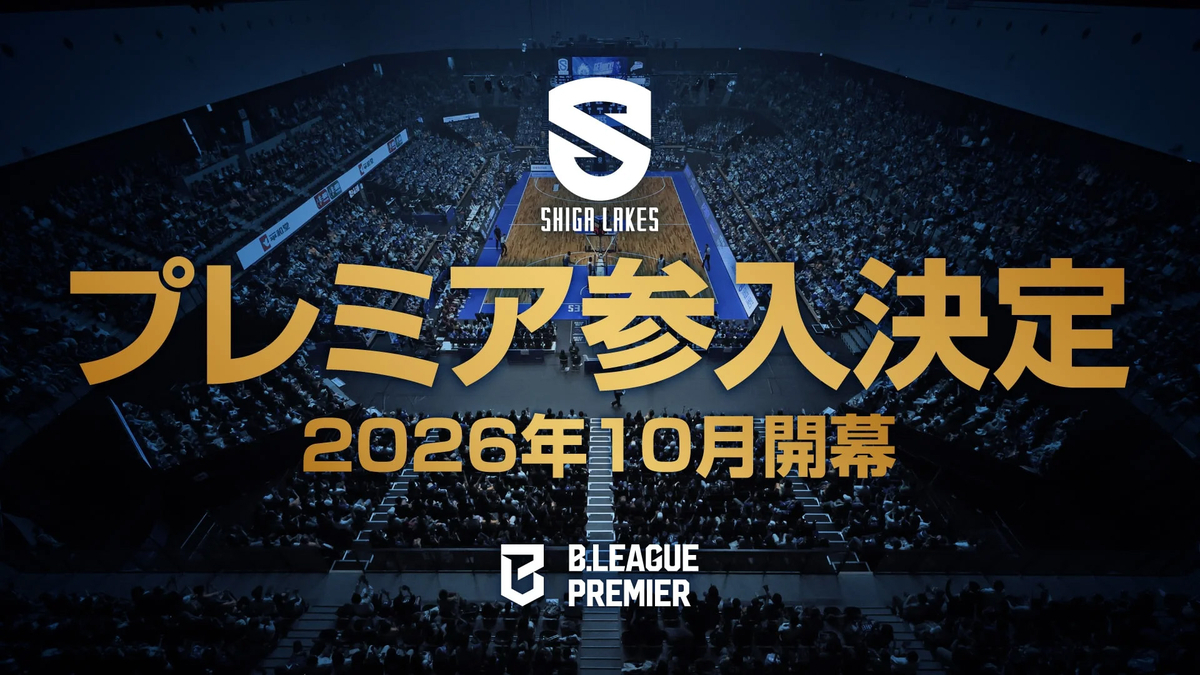
「新ゴ」を使った制作物の一例
「滋賀レイクス」は、株式会社滋賀レイクスターズが運営するプロバスケットボールチームで、現在はB1リーグに所属している。
2022年に実施したリブランディングに伴い欧文のオリジナルフォントを作成、これに合わせて使う和文フォントとして、モリサワの新ゴを採用し、社内外のクリエイティブで活用している。
新ゴは、装飾のない均質で明るいデザインの現代的なゴシック体で、モリサワを代表するフォントのひとつです。広告から公共のサインなど幅広いシーンで使われており、フォントの太さを表す「ウエイト」は8種類の展開があり、滋賀レイクスではこの8種類をオフィシャルフォントとして採用している。
▼ビジョンマップと今シーズン選手プロフィールPOP
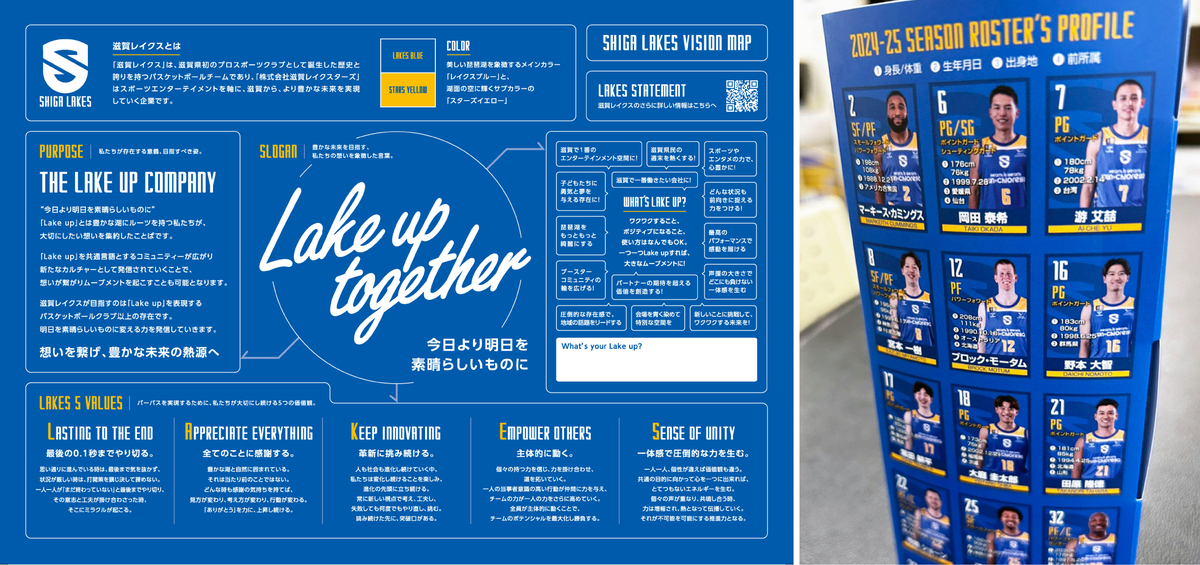
リブランディングやフォント指定の狙いから社内外における新たなブランドイメージの浸透効果について、滋賀レイクスのコミュニケーションデザイン室およびパートナー部のインタビューも公開されている。